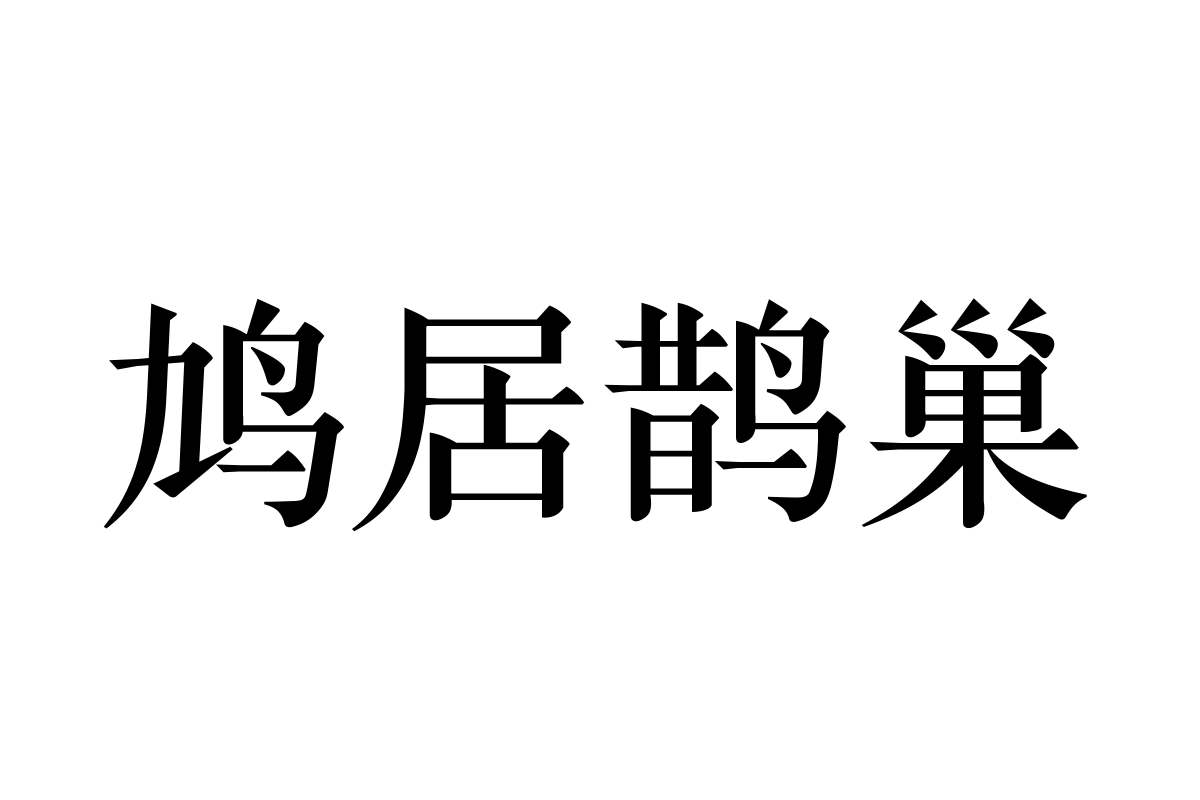
汉仪金陵刻经 W 是一款由汉仪字库出品的商业字体,主要适用于艺术设计、平面宣传设计、网页设计以及书法字帖等领域。以下是对该字体的具体介绍:
2. **字符与风格**
– **字符数量**:该字体包含9883个字符,涵盖了基本拉丁文、拉丁文扩充系列、希腊文和科普特文等。
– **风格样式**:字体风格为W,笔触粗细适中,书写端正,适合多种应用场景。
3. **适用领域**
– **艺术设计**:由于其书写端正的特点,非常适合用于艺术设计领域,如海报、插画等。
– **平面宣传设计**:可用于广告、杂志封面等平面宣传设计,增强视觉效果。
– **网页设计**:在网站设计中,可以用于标题、按钮等元素,提升页面的整体美感。
– **书法字帖**:对于学习书法的用户,此字体也是一个很好的选择,有助于提高书写技巧和审美水平。
综上所述,汉仪金陵刻经 W 字体以其独特的艺术风格和广泛的应用场景,成为设计师们不可或缺的字体之一。无论是在专业设计还是个人创作中,合理利用这款字体,都能带来意想不到的效果。